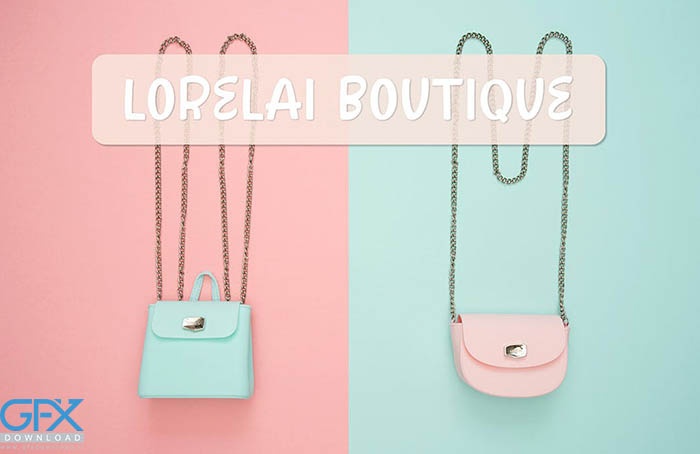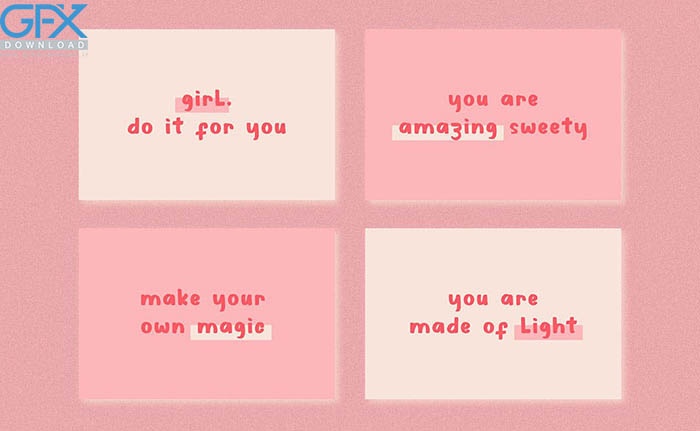
فونت رایگان انگلیسی Arabhella
فونت انگلیسی بامزه Arabhella
دانلود رایگان فونت انگلیسی بامزه Arabhella
Arabhella یک فونت دست نویس زیبا و سرگرم کننده است. ظاهر جذاب، بازیگوش و بچه‌گانه آن، آن را به انتخابی فوق‌العاده برای مد، امضا، لوگوهای جلد آلبوم، برندسازی، مجلات، پست‌های رسانه‌های اجتماعی، تبلیغات و بسیاری موارد دیگر تبدیل می‌کند. از این فونت برای اضافه کردن به هر ایده طراحی که فکر می کنید استفاده کنید! فونت رایگان انگلیسی Arabhella را در ادامه مطلب با لینک مستقیم می توانید دریافت کنید.
• مجموعه کاراکتر
• اعداد و علائم نگارشی (OpenType Standard)
• لهجه ها (نویسه های چند زبانه)